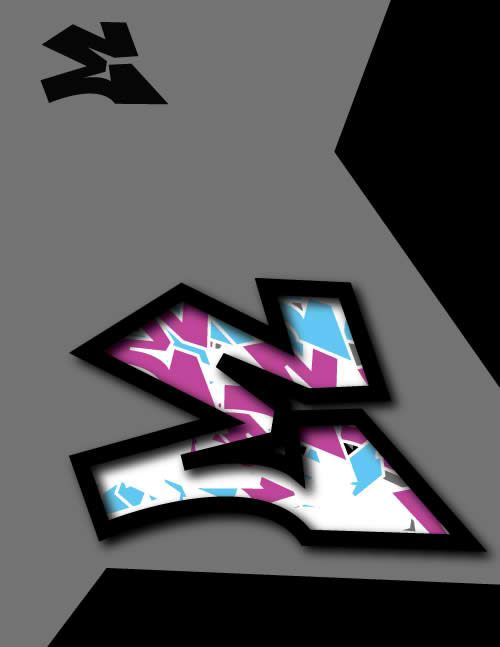
Граффити Буква E Учебник по рисованию
Научитесь рисовать граффити-букву E маркерами
Работа с одной буквой за раз — отличный способ попрактиковаться в рисовании граффити.
Сегодня мы собираемся нарисовать граффити-букву E.
Вы можете использовать этот урок в качестве практического упражнения или использовать свои рисунки как самостоятельные произведения искусства. Любой из них хорош, и оба подхода полезны для улучшения вашего искусства и навыков рисования.
Работа над отдельными буквами — хороший способ попрактиковаться в цветовых сочетаниях и стилях фона. Вы можете сделать серию рисунков граффити с буквой E и придумать кучу новых дизайнов.
ship Sketing Elketh Elketch Elketch Elketch. это отличный способ разогреться и проработать некоторые грубые идеи. При наброске ваших идей для граффити-рисунков с буквой E вам нужно только уловить поток буквы. Пока не беспокойтесь о добавлении каких-либо деталей.
И не тратьте на это много времени. Три-пять минут — это все, что вам действительно нужно для завершения этого шага. Цель состоит в том, чтобы расслабиться и получить некоторые основные идеи для ваших рисунков.
Вы можете использовать эталонные фотографии или попробовать придумать свой собственный стиль надписей. Если вы только начинаете, вам, вероятно, понадобятся фотографии, которые помогут вам начать.
Граффити Буква E Рисование шаг за шагом
Первый шаг при рисовании чего-либо — это создание простых фигур и направляющих линий. Во-первых, это значительно упрощает начало работы. Это поможет вам сделать первые отметки на чистом листе бумаги. И это дает вам приблизительное представление о том, как будет выглядеть ваш рисунок.
Это также отличный способ получить размер и форму вашего рисунка, прежде чем вы потратите слишком много времени на работу над ним.